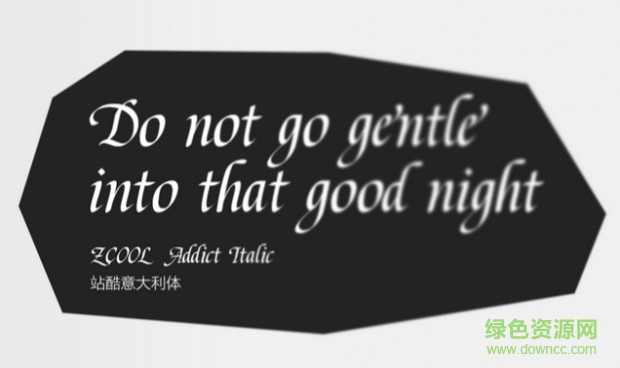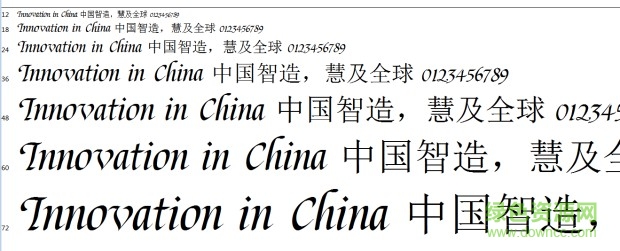
站酷意大利字體
站酷意大利體字體是一款非常優(yōu)雅的字體,這款字體是站酷字體中的首款西文字體,也是深受超多人喜愛哦,可以免費(fèi)下載使用的,感興趣的朋友就來綠色資源網(wǎng)下載體驗(yàn)吧!
站酷意大利字體介紹
[ZCOOL Addict Italic]站酷意大利體是由大貓Addict設(shè)計(jì),站酷冠名的首款公益西文字庫, 是可免費(fèi)商用的西文字,2016年5月發(fā)布第一版。
站酷意大利體預(yù)覽